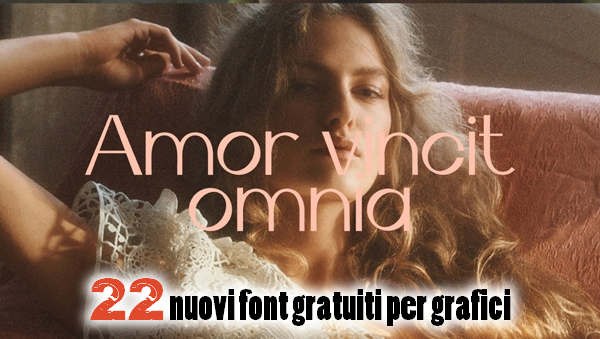
Sul sito Graphic Design Junction vi segnalo una bella raccolta di font gratuiti per grafici.
I font, tutti molto professionali, sono perfetti per loghi, inviti, design di matrimoni, post sui social media, poster pubblicitari, packaging di prodotti, design di prodotti, etichette, fotografia, filigrane, eventi speciali e molto altro.
22 nuovi font gratuiti per grafici